Font chữ không chân luôn được ưa chuộng trong thiết kế nhờ vẻ hiện đại, dễ đọc và tính ứng dụng cao. Tuy nhiên, để có thể sử dụng trọn bộ font không chân tiếng Việt đầy đủ và hiển thị đúng dấu, người dùng cần tải và cài đặt đúng cách. Bài viết này, Vietkey sẽ hướng dẫn chi tiết cách tải font chữ không chân tiếng Việt full, giúp bạn dễ dàng sử dụng trong mọi dự án thiết kế, trình bày và soạn thảo văn bản.
Thế nào là font chữ không chân?
Font chữ không chân, hay còn gọi là sans-serif, là kiểu chữ không có các nét gạch nhỏ ở đầu hoặc cuối của mỗi ký tự. Đặc điểm nổi bật của loại font này là các đường nét đơn giản, thẳng và dứt khoát, tạo cảm giác hiện đại và tối giản. Nhờ sự rõ ràng và dễ đọc, font chữ không chân thường được sử dụng rộng rãi trong thiết kế web, ứng dụng di động, hoặc các ấn phẩm kỹ thuật số, nơi người xem tiếp xúc qua màn hình điện tử.
Một số font không chân phổ biến có thể kể đến như Arial, Helvetica, Roboto, Open Sans hay Verdana. So với font có chân (serif) mang phong cách truyền thống và trang trọng, font không chân thể hiện sự trẻ trung, năng động và phù hợp với xu hướng thiết kế hiện đại. Chính sự tối giản và hiệu quả trong truyền tải thông tin đã khiến sans-serif trở thành lựa chọn hàng đầu trong các thiết kế đề cao tính trực quan và dễ nhìn.
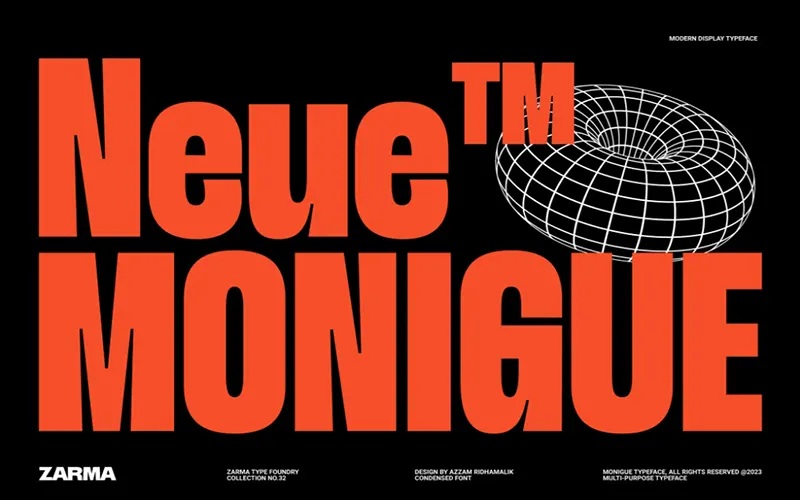
Các font chữ không chân phổ biến hiện nay
Font chữ không chân ngày càng được ưa chuộng trong thiết kế hiện đại nhờ sự tối giản và dễ đọc. Dưới đây là những font sans-serif phổ biến nhất hiện nay, được sử dụng rộng rãi trong cả in ấn lẫn thiết kế kỹ thuật số.
Futura
Futura là một trong những font chữ không chân nổi tiếng nhất, được thiết kế bởi Paul Renner vào năm 1927. Font này mang phong cách hình học với các đường nét tròn đều, cân đối và hiện đại, thể hiện tinh thần của chủ nghĩa hiện đại thế kỷ 20. Nhờ vẻ ngoài tối giản nhưng mạnh mẽ, Futura thường được sử dụng trong thiết kế logo, poster, quảng cáo và các thương hiệu muốn truyền tải sự chuyên nghiệp, tiên phong và sáng tạo.
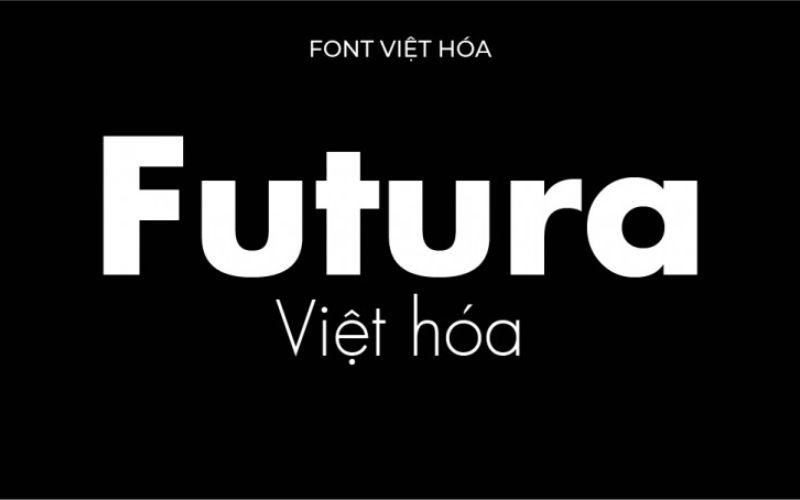
Helvetica Now
Helvetica Now là phiên bản nâng cấp của font chữ Helvetica huyền thoại, được tối ưu để hiển thị hoàn hảo trên cả bản in và màn hình kỹ thuật số. Với thiết kế cân đối, đường nét tinh tế và độ sắc nét cao, Helvetica Now mang lại cảm giác hiện đại và sang trọng. Nhờ đó, font chữ này trở thành lựa chọn hàng đầu trong các dự án nhận diện thương hiệu, thiết kế cao cấp và ấn phẩm đòi hỏi tính thẩm mỹ tinh gọn.
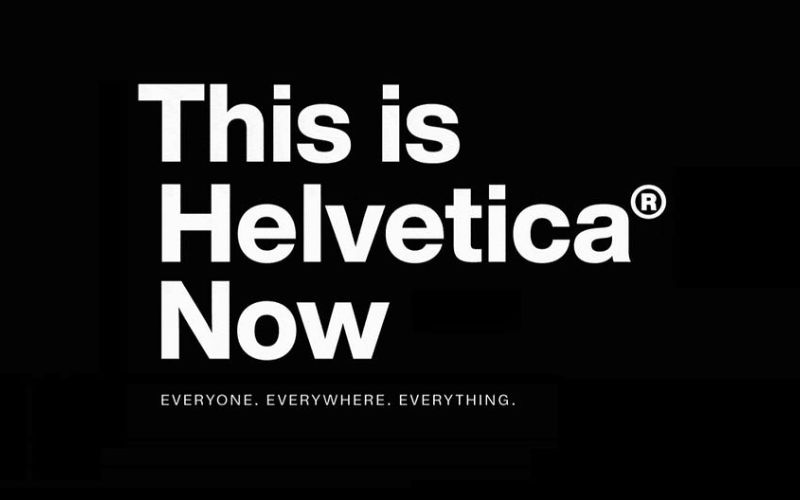
Arial
Arial là một font chữ không chân phổ biến, được phát triển vào năm 1982 bởi Robin Nicholas và Patricia Saunders cho hãng Monotype. Font này nổi bật với các đường nét mềm mại, cân đối và dễ đọc, phù hợp cho cả văn bản in lẫn hiển thị trên màn hình. Nhờ tính linh hoạt và khả năng tương thích cao, Arial được sử dụng rộng rãi trong các tài liệu văn phòng, website, quảng cáo và hệ thống nhận diện thương hiệu trên toàn thế giới.
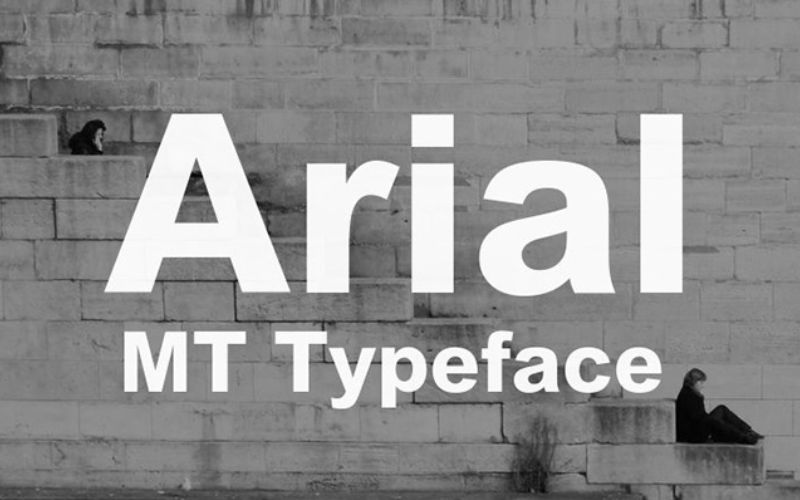
Calibri
Calibri là font chữ không chân được giới thiệu lần đầu vào năm 2007 và nhanh chóng trở thành mặc định trong bộ Microsoft Office. Với thiết kế bo tròn nhẹ ở các góc và đường nét mềm mại, Calibri mang lại cảm giác thân thiện, hiện đại và dễ đọc. Font này được ưa chuộng trong môi trường công sở, bài thuyết trình và các tài liệu chuyên nghiệp nhờ khả năng hiển thị rõ ràng trên cả màn hình lẫn bản in.
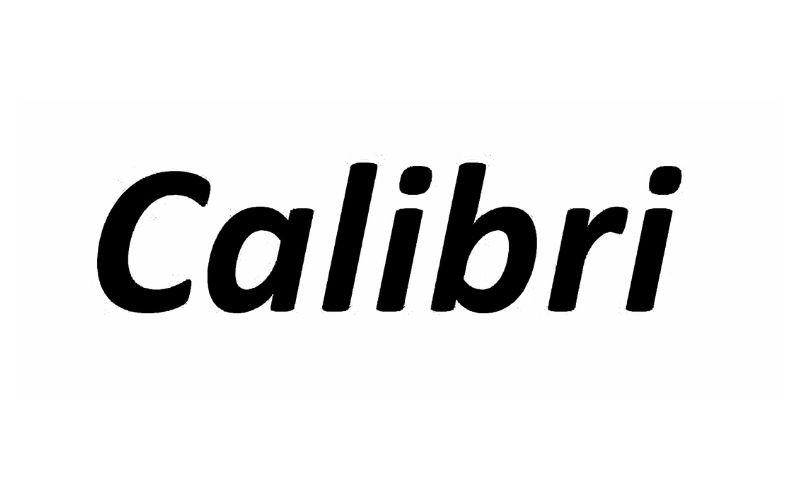
Roboto
Roboto là font chữ không chân được Google phát triển vào năm 2011, thiết kế riêng cho hệ điều hành Android. Font này kết hợp giữa phong cách hình học hiện đại và sự mềm mại trong từng đường cong, giúp dễ đọc ở mọi kích thước hiển thị. Nhờ tính cân đối, linh hoạt và khả năng tương thích cao, Roboto hiện là một trong những font sans-serif phổ biến nhất trong thiết kế web, giao diện người dùng và các sản phẩm công nghệ.
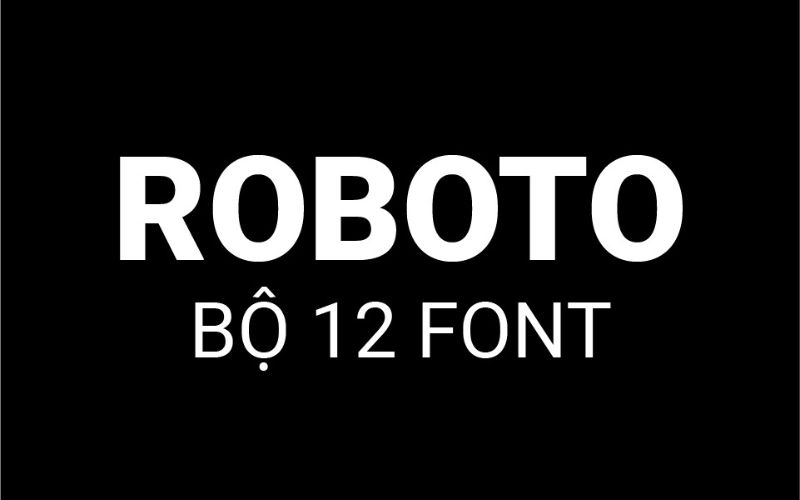
Open Sans
Open Sans là font chữ không chân do Steve Matteson thiết kế, được tối ưu hóa cho khả năng đọc rõ ràng trên cả màn hình kỹ thuật số và bản in. Với các đường nét mở, cân đối và thân thiện, Open Sans mang lại cảm giác chuyên nghiệp nhưng vẫn gần gũi. Nhờ tính linh hoạt cao, font này được sử dụng phổ biến trong thiết kế website, giao diện ứng dụng, tài liệu doanh nghiệp và hệ thống nhận diện thương hiệu hiện đại.
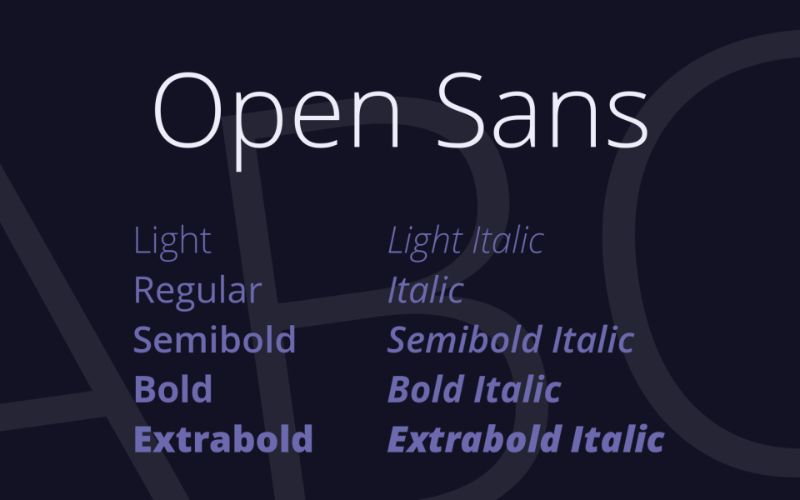
Quicksand
Quicksand là font chữ không chân mang phong cách hình học, được thiết kế bởi Andrew Paglinawan vào năm 2008. Font này có các đường nét bo tròn mềm mại, tạo cảm giác thân thiện, hiện đại và dễ tiếp cận. Nhờ sự cân đối và tinh tế trong từng chi tiết, Quicksand thường được sử dụng trong thiết kế website, poster, logo và các dự án hướng đến sự trẻ trung, sáng tạo và tối giản.
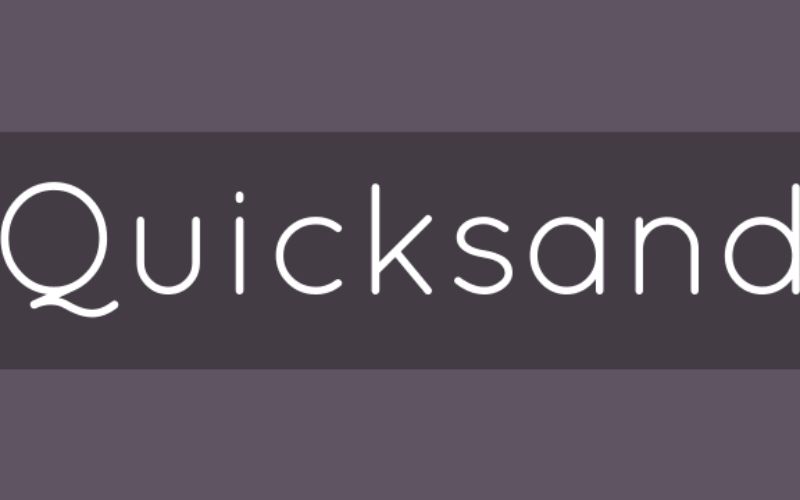
Peace Sans
Peace Sans là font chữ không chân mang phong cách đậm nét, mạnh mẽ và hiện đại. Với thiết kế chữ dày, bo tròn nhẹ ở các góc, font này tạo cảm giác thân thiện nhưng vẫn thể hiện sự tự tin và nổi bật. Peace Sans thường được sử dụng trong thiết kế logo, tiêu đề, poster quảng cáo hoặc các dự án cần gây ấn tượng mạnh về mặt thị giác, đặc biệt phù hợp với phong cách thiết kế trẻ trung và năng động.